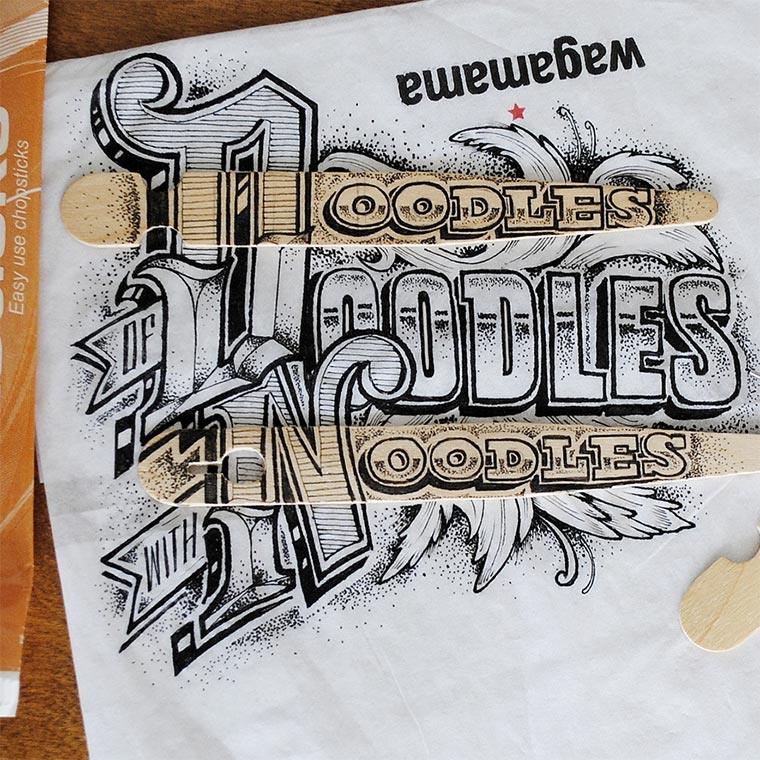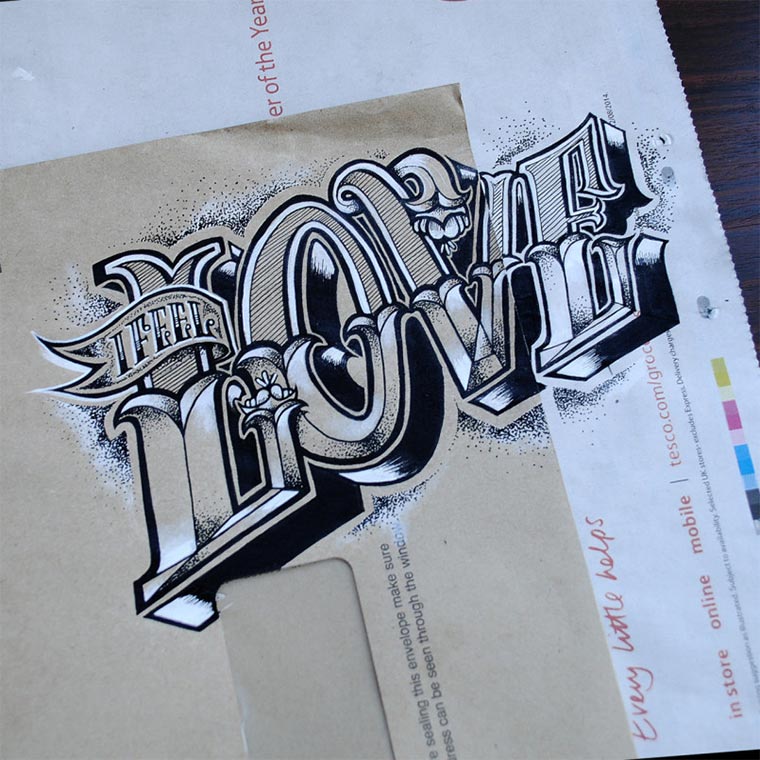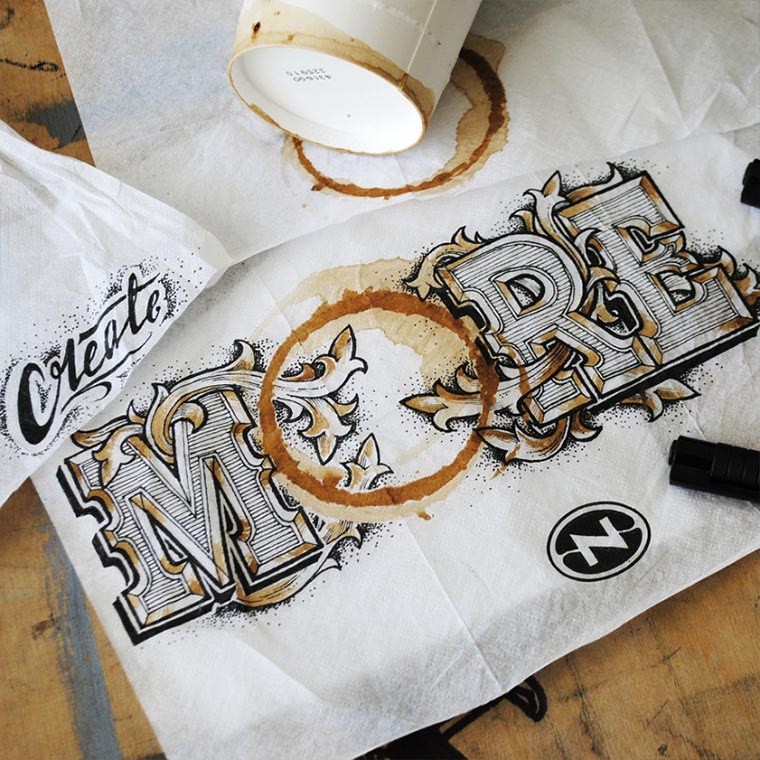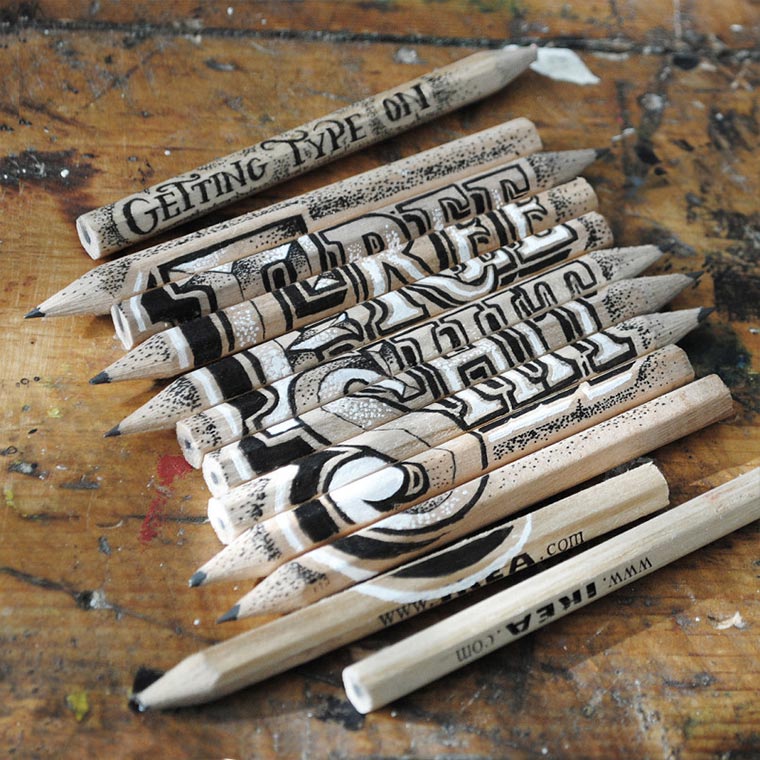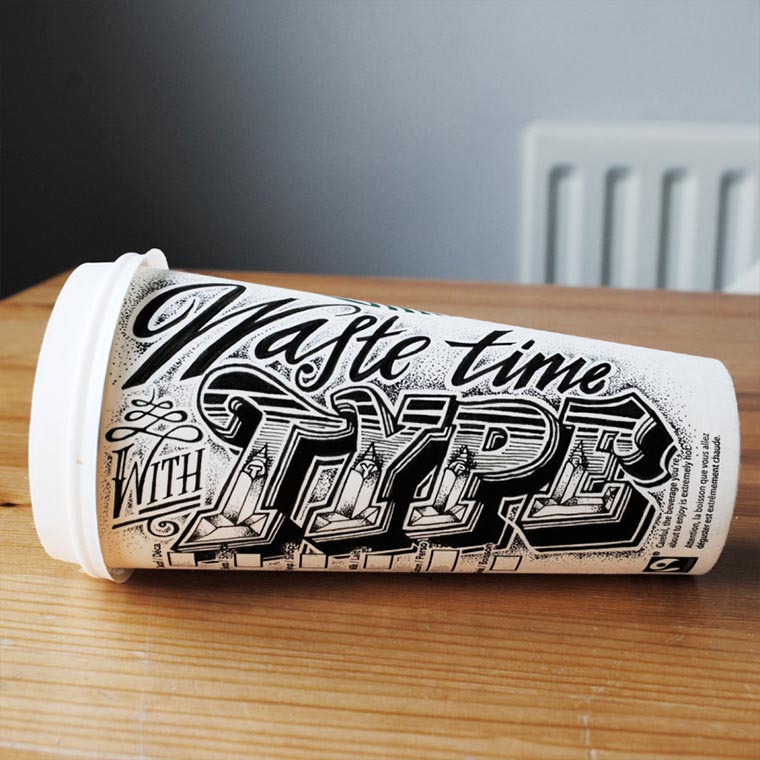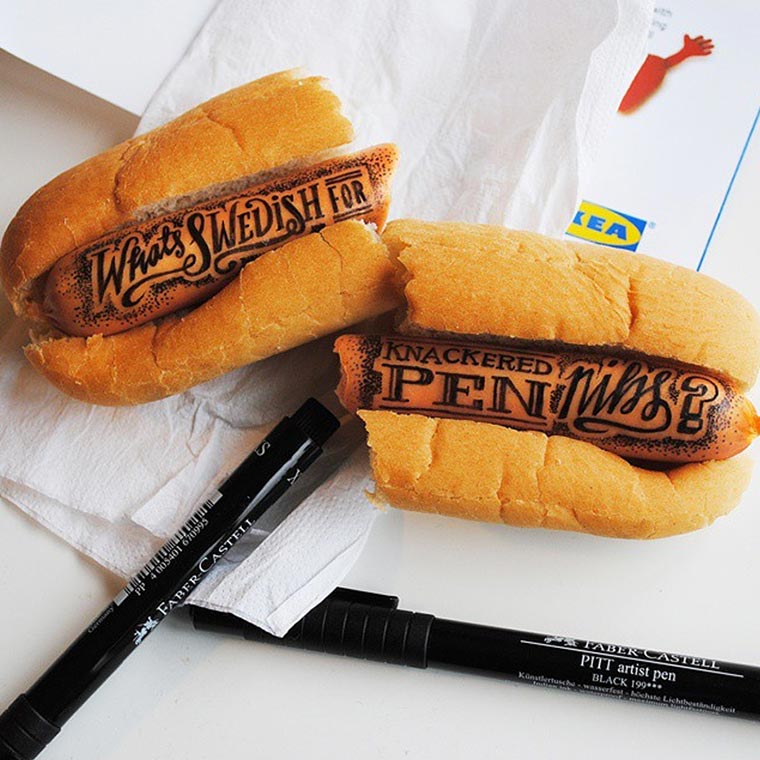
Lettering Everything
Typografie: Rob Draper
Rob Draper muss einfach ein Bruder von Don Draper sein. Anders ist die Kreativität des Freelance Illustrators aus UK nicht zu erklären. Der zeichnet nämlich nicht nur tolle Typografie-Arbeiten auf Papier, sondern auch auf Pappbechern, Stiften oder Bockwürsten. Ja, richtig gelesen. Alles, nur nicht langweilig.